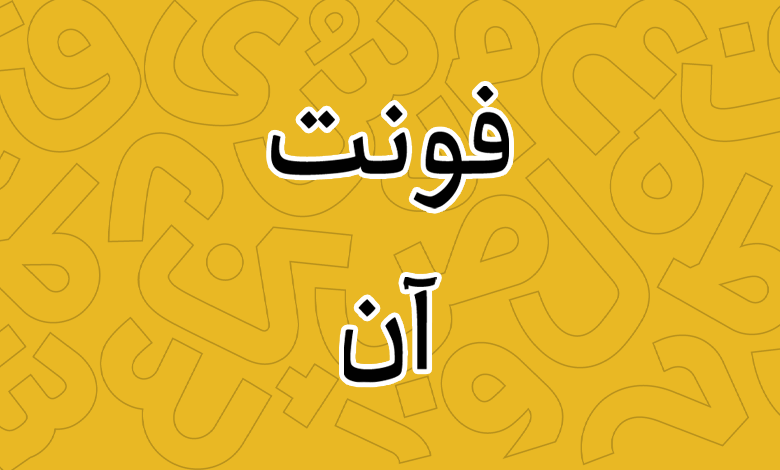
فونت آن (ON)
فونت آن (به انگلیسی: ON) از قلم‌های خاص به سبک خط نسخ است که طی یک همکاری دو طرفه توسط امیر مصباحی و نیاز میرمبینی در قالب یک پروژه مشترک با هدف تمرکز روی یافتن سبک جدیدی از تایپ فیس ویژه مطبوعات در فضای دیجیتال ساخته شده است.
هدف از ساخت فونت این بوده که در صفحات نمایشی همچون موبایل، تبلت و دسکتاپ که این روزها به بخش جدایی ناپذیر از زندگی روزمره افراد مختلف تبدیل شده‌اند، سبک خاصی برای فونت مطبوعات یافته شود که خوانایی و کارکرد لازم را در این حوزه داشته باشد.
یکی از مسائل مهمی که در فونت‌های مناسب برای مطبوعات می‌بایست رعایت گردد، فراهم آوردن تنوع قلم در کنتراست پوینت‌ها، ضخامت حروف، سبک و ساختار طراحی قلم در وزن‌های مختلف است.
با اینکه بیشتر فونت‌ها با افزایش وزن تغییرات جزئی در بخش‌های مختلف را با نسبت بسیار نزدیکی دارند، اما در فونت‌های مطبوعاتی باید روی این مسئله بازبینی‌هایی را انجام داد.
سبک طراحی و وزن فونت آن
فونت آن با تمرکز بر روی ایجاد تنوع در کنتراست ضخامت حروف و پوینت سایز استاندارد، سبک و ساختار این قلم را در وزن‌های مختلف متغیر کرده تا در کاربردها و سایزهای گوناگون بهترین عملکرد و کیفیت را به نمایش بگذارد.
لذا با انجام تست‌های متعددی که روی پرینت صفحات نمایشی توسط این قلم صورت گرفته و با سایر قلم‌ها مقایسه شده است، در نهایت ۳ پوینت استاندارد در تمامی وزن‌های این قلم شکل گرفته که خوانش قابلیت تشخیص فونت را در اندازه‌ها، عناوین و بخش‌های مختلف با توجه به تغییر وزن ساده کرده است.
این فونت از ۶ وزن نازک تا سیاه را پشتیبانی می‌کند و با توجه به ساختاری که برای طراحی حروف آن درنظر گرفته شده یک فونت خاکستری است.
پشتیبانی از ۵ زبان متنوع
فونت آن با تمرکز بر روی زبان فارسی طراحی و توسعه یافته است. اما در همان ابتدا زبان انگلیسی و عربی نیز برای آن در نظر گرفته شد تا لزومی به تغییر قلم در استفاده‌های چندزبانه نباشد.
اما در این بین خلا در قلم احساس میشد که آن هم کم‌توجهی بسیاری قلم‌ها است که به زبان کردی وجود داشته است. لذا این قلم برای استفاده در زبان کوردی نیز توسعه داده شد تا گلیف‌ها و استانداردهایی که برای اعراب گذاری برای این زبان وجود دارد نیز در آن پیاده‌سازی شود.
در فونت آن کلیه اعراب اصلی در هم‌نشینی مناسبی با سایر کاراکترهای «سکون، همزه، تشدید» قرار می‌گیرند و با توجه به سبک وزنی که برای اعراب در نظر گرفته شده باعث نمایشی‌تر شدن کلمات در وزن‌های مختلف خواهند شد که چنین ساختاری در فونت مطبوعات به خوانش بهتر متن کمک می‌کند.
دیگر زبان پشتیبانی شده این قلم اردو است که حروفی همچون «ﮧ، ﮩ، ے» و همچنین گلیف‌های تزئینی و طره‌ها را که در این زبان نیز مانند زبان کردی زیاد کاربرد دارد پشتیبانی می‌کند. همچنین از برخی حروف مانند «ے» پایانی به عنوان حرف جایگزین می‌توان استفاده کرد.
این قلم همچنین از زبان انگلیسی با همان سبک طراحی پشتیبانی می‌کند که تمامی حروف همان حالت جدی، زاویه خاص و شکستگی ناگهانی برخی حروف در منحنی‌ها را دارند.
دارای حروف جایگزین و ترکیبات مرکب
به منظور استفاده بهتر این قلم در کارهای گرافیکی و نمایشی که می‌تواند در حوزه تبلیغات و همچنین چاپ، به‌ویژه طراحی جلد کتب، مجلات و پوسترها مورد استفاده قرار گیرد، برخی حروف و ترکیبات دارای حالت جایگزین هستند.
همانطور که در تصویر زیر می‌بینید، می‌توانید در ترکیباتی همچون «ـی، ـر، ـن، گ» شکل حروف را متفاوت از حالت معمول تایپ کنید که باعث ایجاد ظاهری متفاوت می‌گردد.
پشتیبانی از گلیف های تزئینی و اعداد فارسی
همانطور که اشاره شد در فونت آن توجه ویژه‌ای به زبان کوردی شده است تا به سهم خود خلا موجود برای این زبان را که در بسیاری فونت‌ها وجود دارد پر کند. برای همین منظور جدای از استاندارد کردن تمامی حروف و ترکیبات بر اساس این زبان، گلیف‌های تزئینی که در این زبان به‌وفور یافت می‌شوند نیز پیاده سازی شده است.
در تصویر بالا نمونه‌ای از متون به زبان کردی، اردو، پشتو، ایغوری و کشمیری را برای فونت آن مشاهده می‌کنید که گلیف‌های تزئینی وام گرفته شده از خط نسخ نیز در آنها به کار رفته است.
ویژگی دیگر این قلم از نظر پشتیبانی گلیف، اعداد فارسی و عربی هستند که طبق استاندارد یونیکد هرکدام دارای گلیف اختصاصی خود هستند. همانطور که در تصویر زیر هم می‌بینید، اعداد عربی «۰۴۵۶» که در مقایسه با اعداد «۰۴۵۶» دارای ظاهری متفاوت هستند، هر یک دارای گلیف خاص خود است. همچنین در نسخه ۲.۰ پشتیبانی از اعداد هم‌عرض به این فونت افزوده شده است.